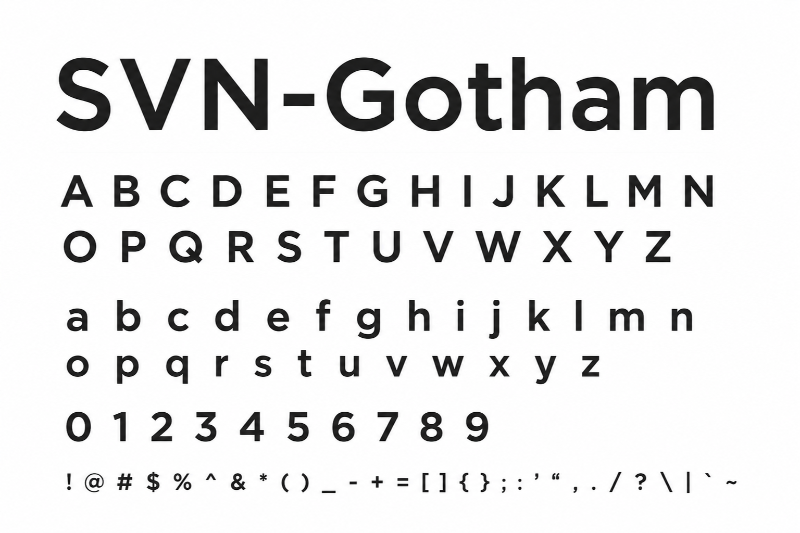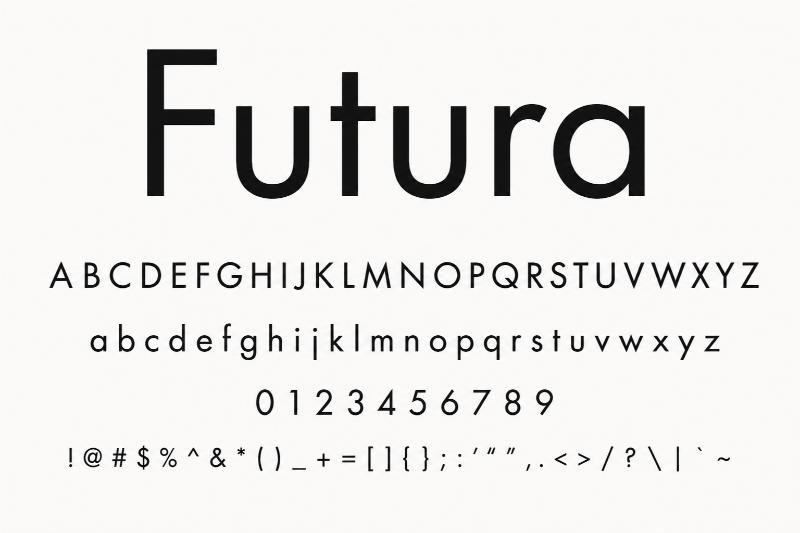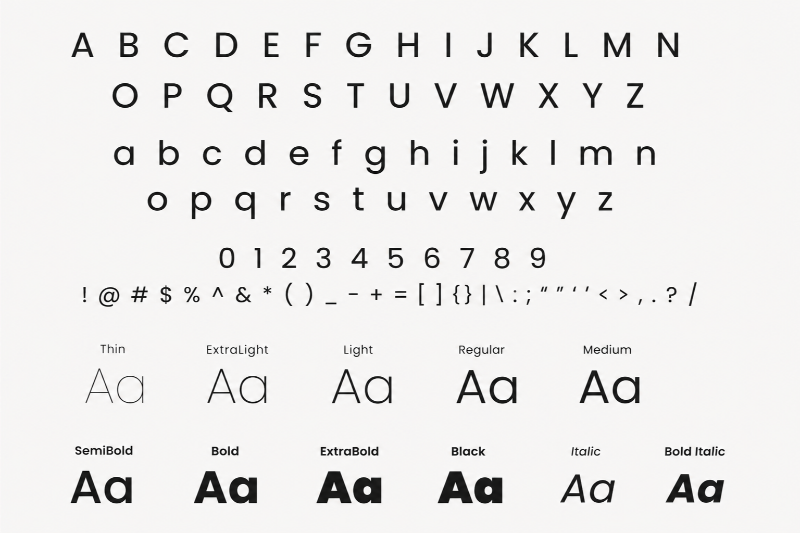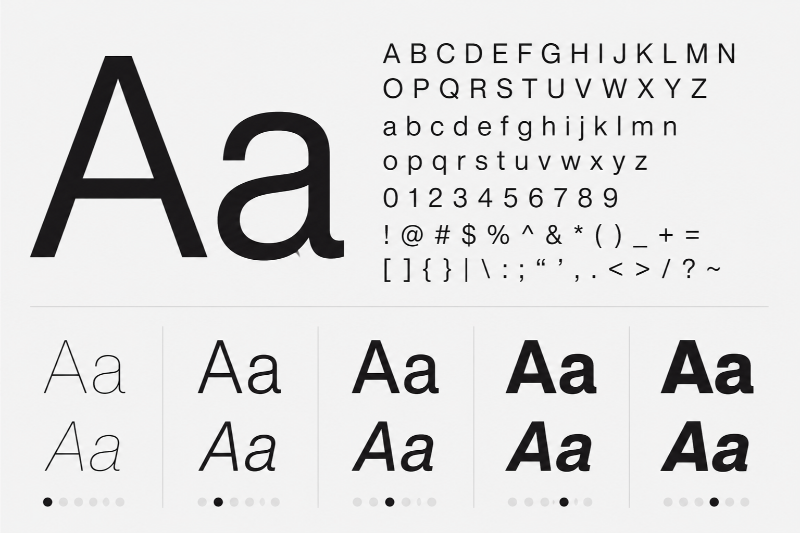
Trong lĩnh vực thiết kế đồ họa, font chữ luôn giữ một vai trò quan trọng hơn nhiều người vẫn nghĩ. Có một câu nói vui nhưng rất đúng rằng: “Một font chữ đẹp có thể nâng tầm cả một thiết kế chưa hoàn hảo, nhưng một font chữ xấu có thể phá hỏng ngay cả bố cục được sắp xếp chỉn chu.” Typography không đơn thuần là phần chữ hiển thị trên thiết kế, mà còn là cảm xúc, cá tính và giọng nói riêng của thương hiệu.
Vậy font chữ không chân, hay Sans-serif, là gì? “Sans” trong tiếng Pháp có nghĩa là “không”, còn “serif” là những nét gạch nhỏ thường xuất hiện ở phần cuối của ký tự. Hiểu đơn giản, font chữ không chân là kiểu chữ đã loại bỏ các nét gạch trang trí này, tạo cảm giác hiện đại, tối giản, rõ ràng và dễ tiếp cận hơn.
Vì sao Font chữ không chân được ưa chuộng trong thiết kế hiện đại?
Khi truy cập các website lớn, sử dụng ứng dụng di động hoặc quan sát logo của những thương hiệu công nghệ hàng đầu như Google, Facebook hay Microsoft, bạn sẽ dễ dàng nhận ra một điểm chung: font chữ không chân xuất hiện rất phổ biến. Vậy lý do nào khiến kiểu chữ này gần như trở thành lựa chọn chủ đạo trong thiết kế hiện đại?
- Tối ưu cho môi trường kỹ thuật số: Font chữ không chân, hay Sans-serif, đặc biệt phù hợp với màn hình máy tính, điện thoại và máy tính bảng. Do màn hình hiển thị bằng hệ thống pixel, các chi tiết mảnh, nét đậm nhạt phức tạp hoặc phần chân chữ của font Serif đôi khi dễ bị nhòe, rối hoặc khó đọc ở kích thước nhỏ. Trong khi đó, font không chân có đường nét gọn gàng, độ dày tương đối đồng đều và cấu trúc rõ ràng, giúp nội dung hiển thị sắc nét hơn, nhất là trong thiết kế giao diện người dùng UI/UX.
- Mang lại cảm giác hiện đại và thân thiện: Về mặt cảm nhận thị giác, font không chân thường tạo ấn tượng trẻ trung, tối giản, cởi mở và dễ tiếp cận. Những đường nét đơn giản, mềm mại hoặc mang tính hình học giúp kiểu chữ này thoát khỏi cảm giác nghiêm túc, nặng nề của các văn bản truyền thống. Vì vậy, Sans-serif thường được các thương hiệu hiện đại lựa chọn để xây dựng hình ảnh năng động, sáng tạo và gần gũi hơn với người dùng.
- Linh hoạt trong nhiều mục đích thiết kế: Một ưu điểm lớn của font chữ không chân là khả năng ứng dụng rất rộng. Kiểu chữ này có thể dùng cho logo thương hiệu, tiêu đề website, poster quảng cáo, giao diện ứng dụng hoặc cả những đoạn nội dung dài. Sans-serif vừa đủ tinh tế để tạo cảm giác chuyên nghiệp, vừa đủ mạnh mẽ để gây chú ý, đồng thời vẫn giữ được độ rõ ràng cần thiết khi trình bày văn bản. Chính sự linh hoạt này khiến font không chân trở thành lựa chọn an toàn và hiệu quả trong nhiều phong cách thiết kế khác nhau.
Top 10+ Font chữ không chân việt hóa đẹp và dễ ứng dụng
Thay vì đưa ra một danh sách font chữ không chân một cách rời rạc, việc phân loại theo mục đích sử dụng thực tế sẽ giúp bạn dễ chọn đúng font hơn. Mỗi font có một cá tính riêng, phù hợp với từng kiểu thiết kế như website, ứng dụng, nhận diện thương hiệu, bài viết dài hay nội dung dành cho giáo dục.
Roboto
Roboto được xem là một trong những font chữ phổ biến nhất hiện nay, đặc biệt trong hệ sinh thái thiết kế của Google. Font này có bố cục chữ thoáng, cân bằng tốt giữa các nét hình học chắc chắn và những đường cong mềm mại. Nhờ khả năng hiển thị rõ ràng ở nhiều kích thước khác nhau, Roboto rất phù hợp cho website, giao diện ứng dụng, màn hình máy tính lẫn thiết bị di động.
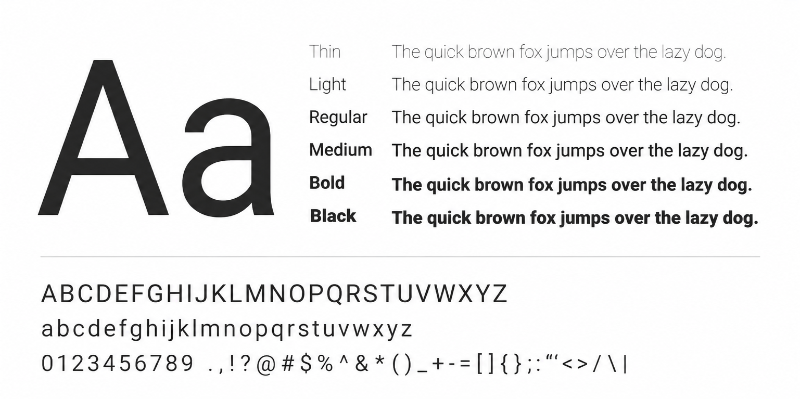
Be Vietnam Pro
Be Vietnam Pro là lựa chọn nổi bật dành riêng cho nội dung tiếng Việt. Ưu điểm lớn nhất của font này nằm ở khả năng xử lý dấu tiếng Việt rất tốt, hạn chế tình trạng dính dấu, lệch dấu hoặc hiển thị thiếu tự nhiên như một số font quốc tế chưa được Việt hóa kỹ. Đây là font phù hợp cho website, tài liệu thương hiệu, thiết kế truyền thông và các dự án cần sự chỉn chu về tiếng Việt.
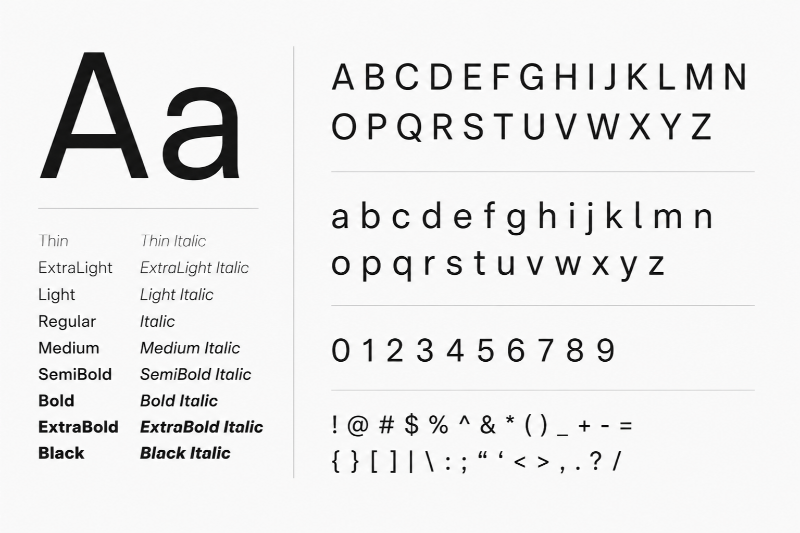
Open Sans
Open Sans là font chữ không chân lý tưởng cho các đoạn nội dung dài. Với đường nét rộng, thoáng và dễ nhìn, font này tạo cảm giác thân thiện, trung tính và không gây mỏi mắt khi đọc lâu. Open Sans đặc biệt phù hợp với blog, website tin tức, landing page hoặc giao diện mobile cần tối ưu trải nghiệm đọc.
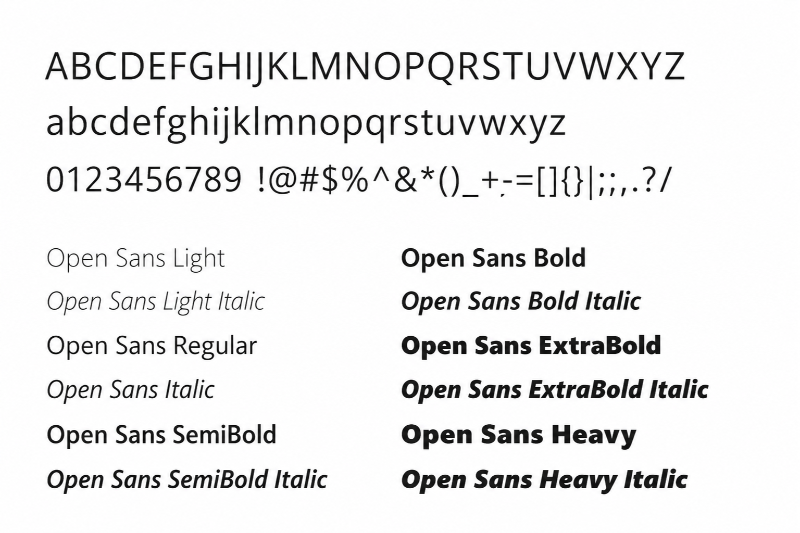
Nunito Sans
Nunito Sans gây ấn tượng nhờ kiểu dáng bo tròn, mềm mại và gần gũi. Font này thường được sử dụng trong các thiết kế hướng đến sự thân thiện, vui tươi hoặc dễ tiếp cận như ứng dụng giáo dục, website dành cho trẻ em, nội dung học tập và các sản phẩm công nghệ có phong cách trẻ trung. Nhờ vẻ ngoài nhẹ nhàng, Nunito Sans giúp thiết kế trở nên bớt khô cứng và dễ tạo thiện cảm với người xem.
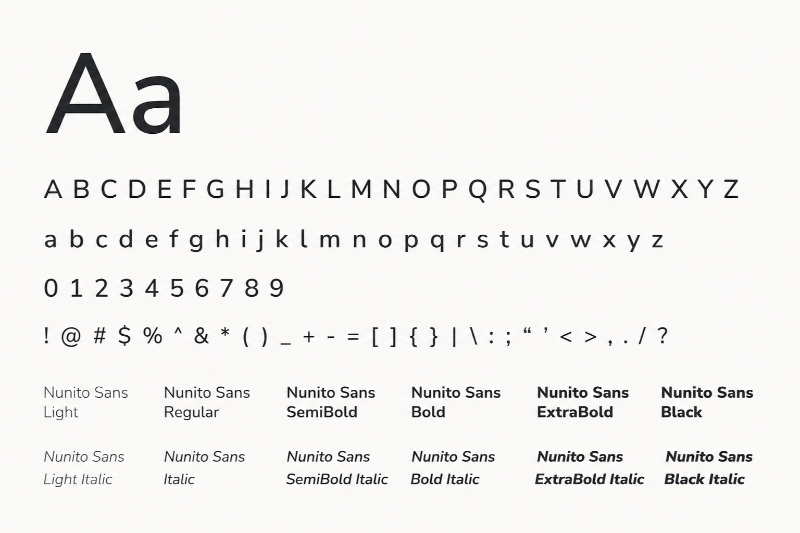
Montserrat
Montserrat là một trong những font chữ không chân được sử dụng rất nhiều trong thiết kế logo và nhận diện thương hiệu. Font này mang vẻ đẹp hiện đại, tinh tế và có khả năng tạo điểm nhấn rất tốt, đặc biệt khi dùng chữ in hoa. Với cảm giác sang trọng nhưng vẫn trẻ trung, Montserrat thường được các thương hiệu thời trang, mỹ phẩm, làm đẹp và lifestyle lựa chọn để xây dựng hình ảnh chuyên nghiệp, cao cấp và dễ ghi nhớ.
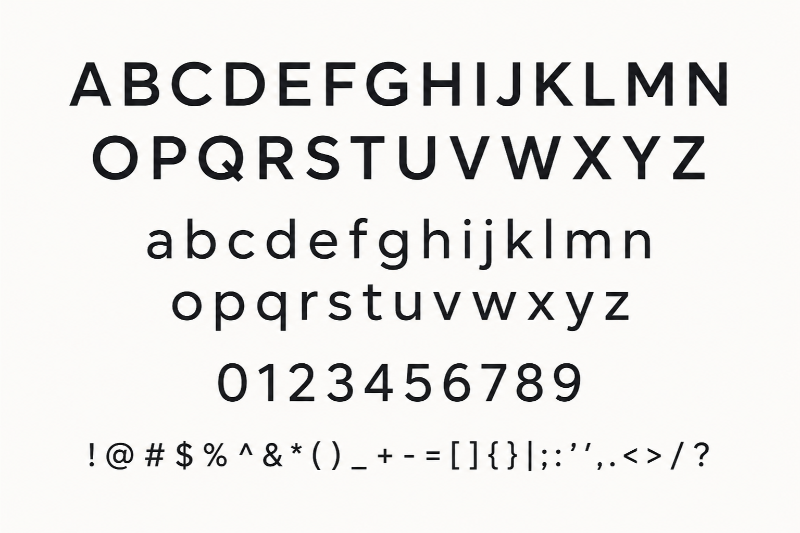
Trên đây là những gợi ý về font chữ không chân việt hóa đẹp, dễ dùng và phù hợp với nhiều nhu cầu thiết kế khác nhau, từ website, logo, poster, banner đến các ấn phẩm truyền thông hiện đại. Hy vọng danh sách này sẽ giúp bạn có thêm lựa chọn chất lượng cho các dự án thiết kế sắp tới.